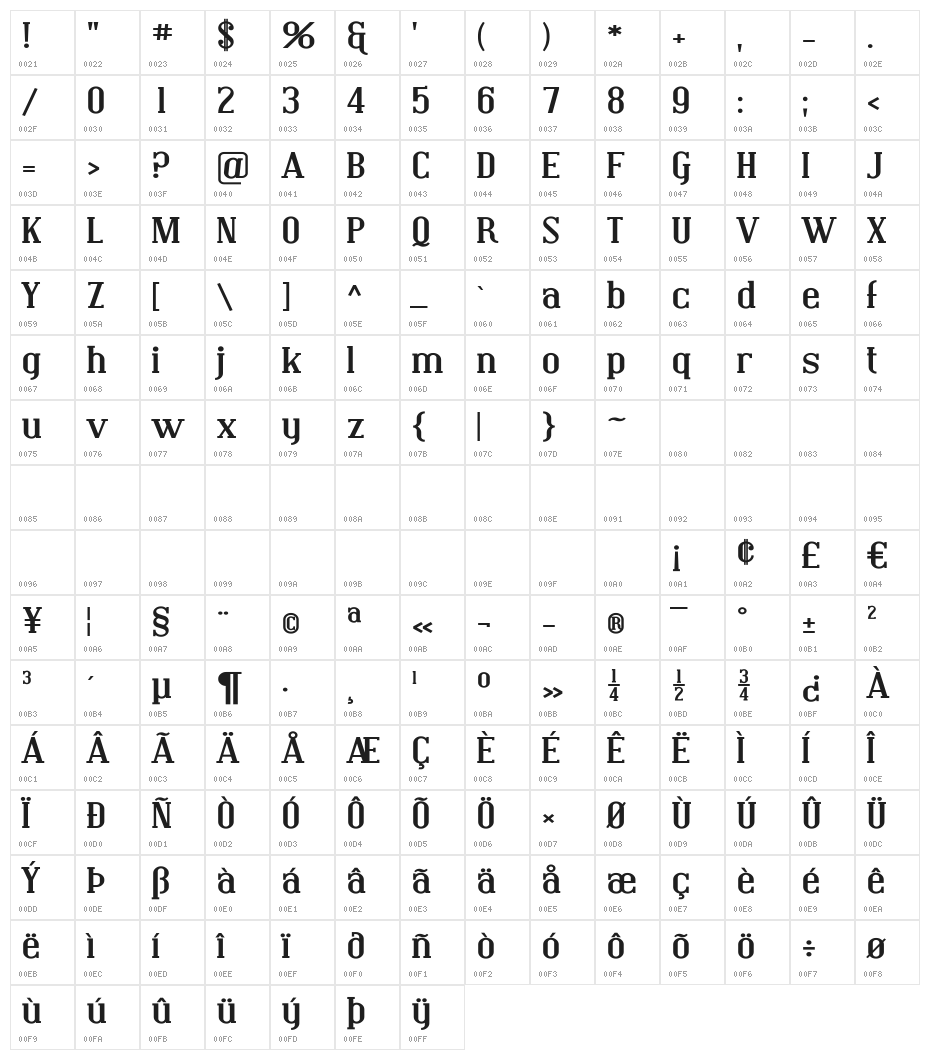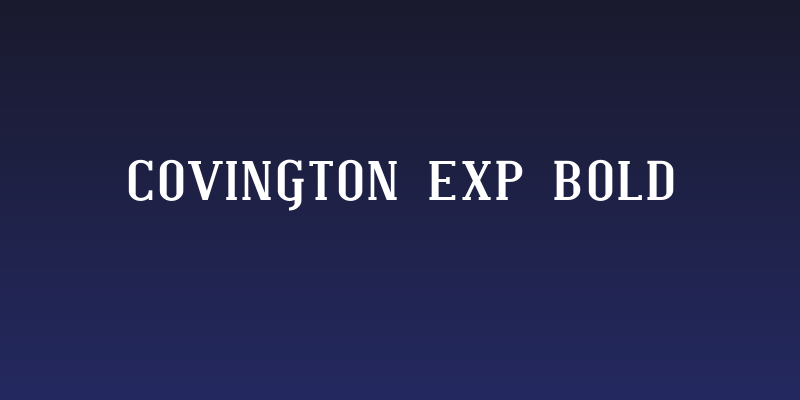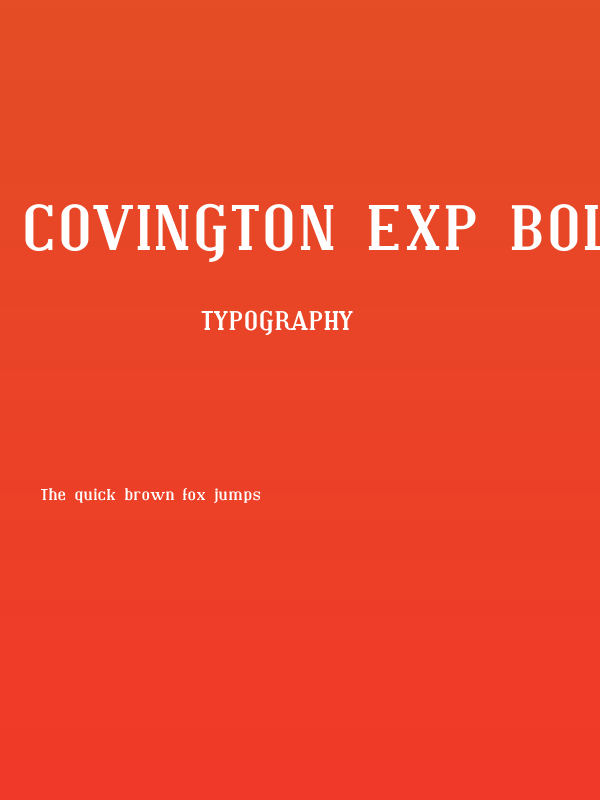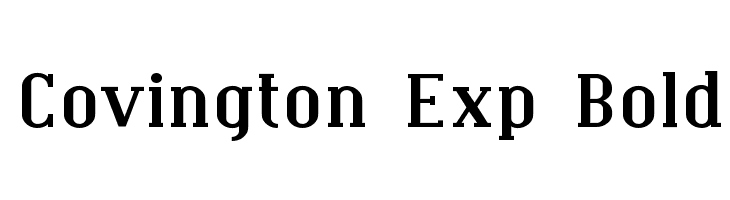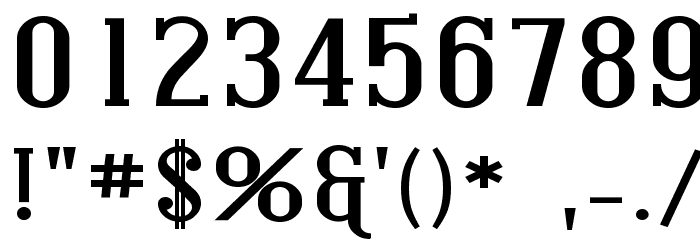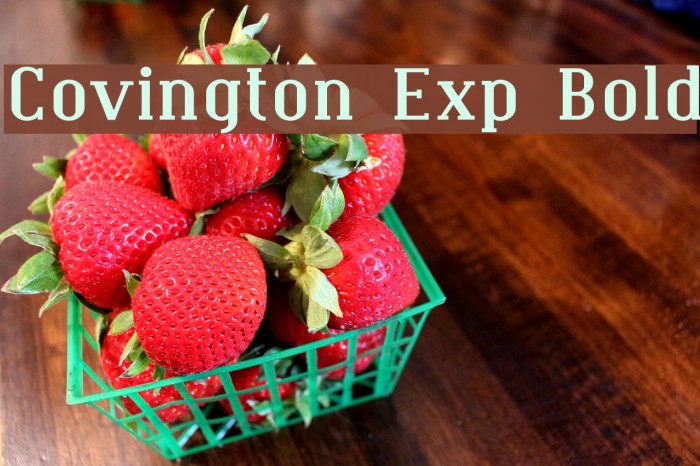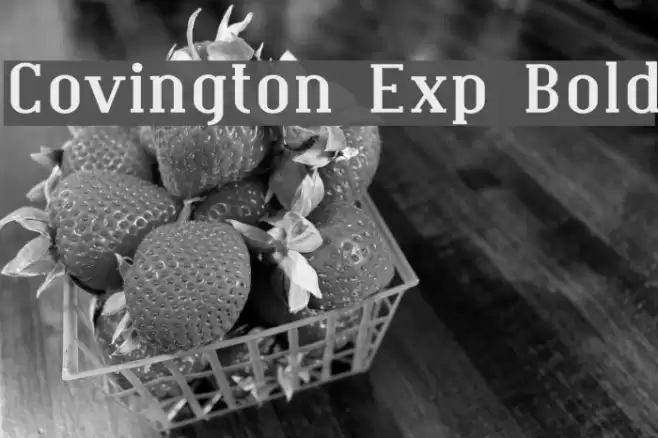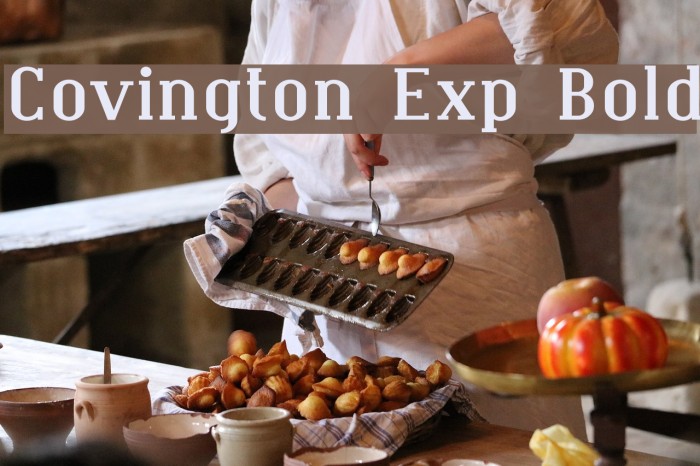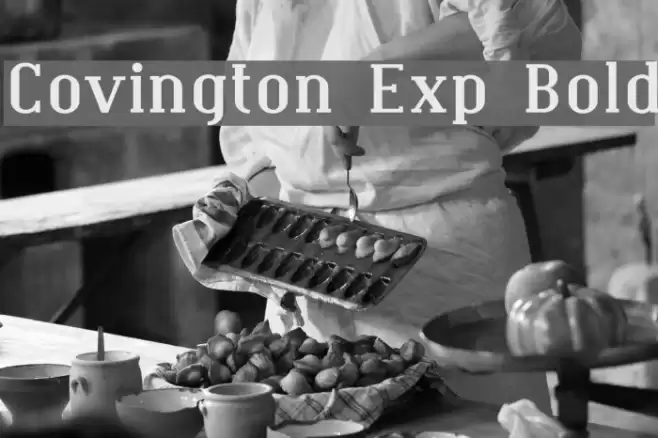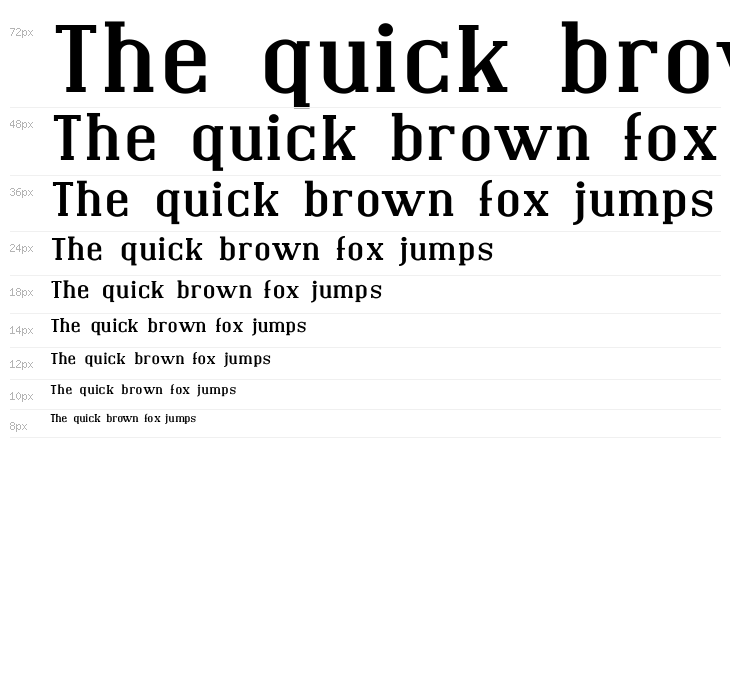
Covington Exp Bold Font
| Categorías | Serif |
| Estilo general | Vintage |
| Proyectos propuestos | Ideal for headlines, posters, branding, and editorial design where a strong, authoritative presence is needed. |